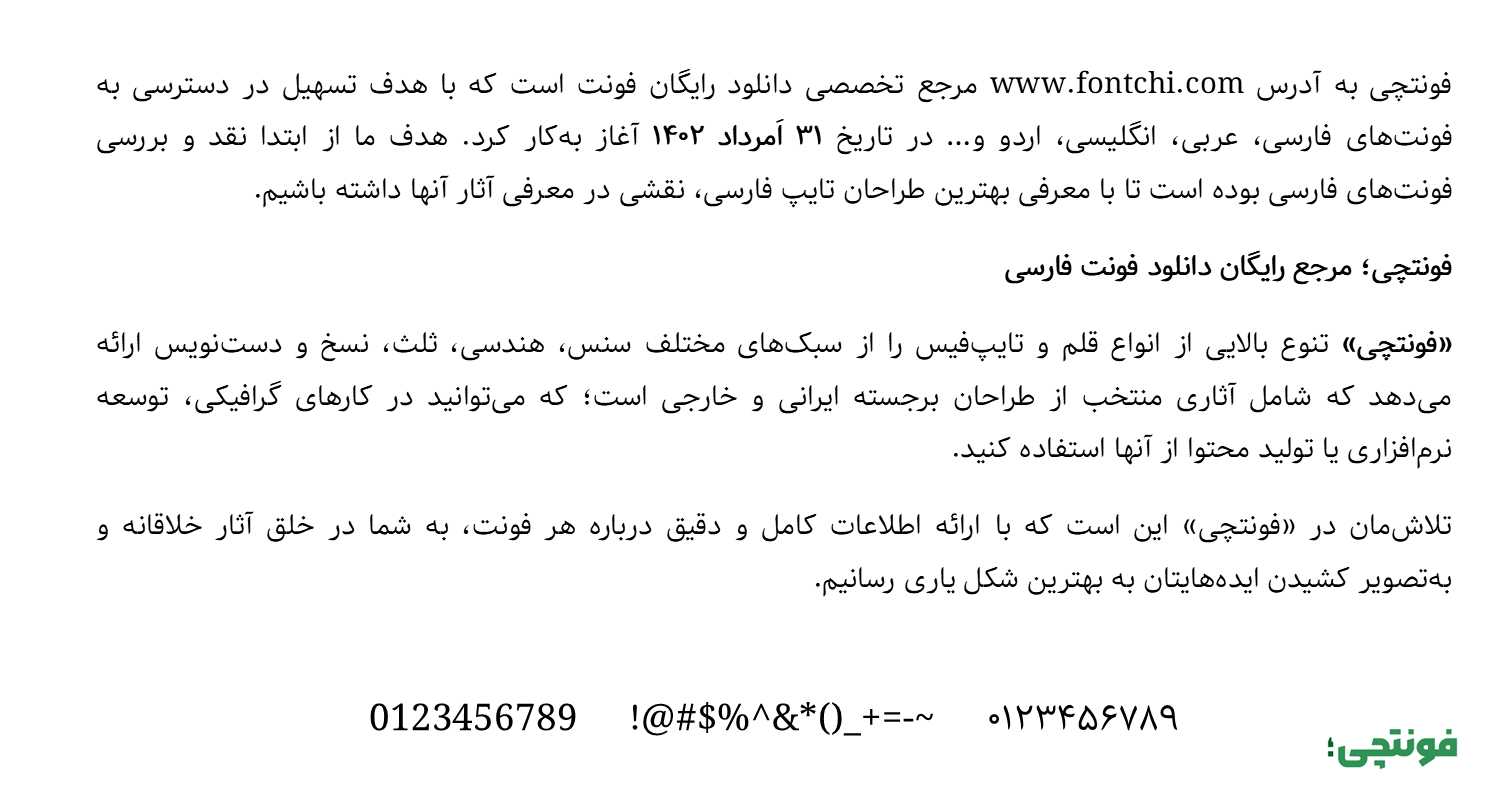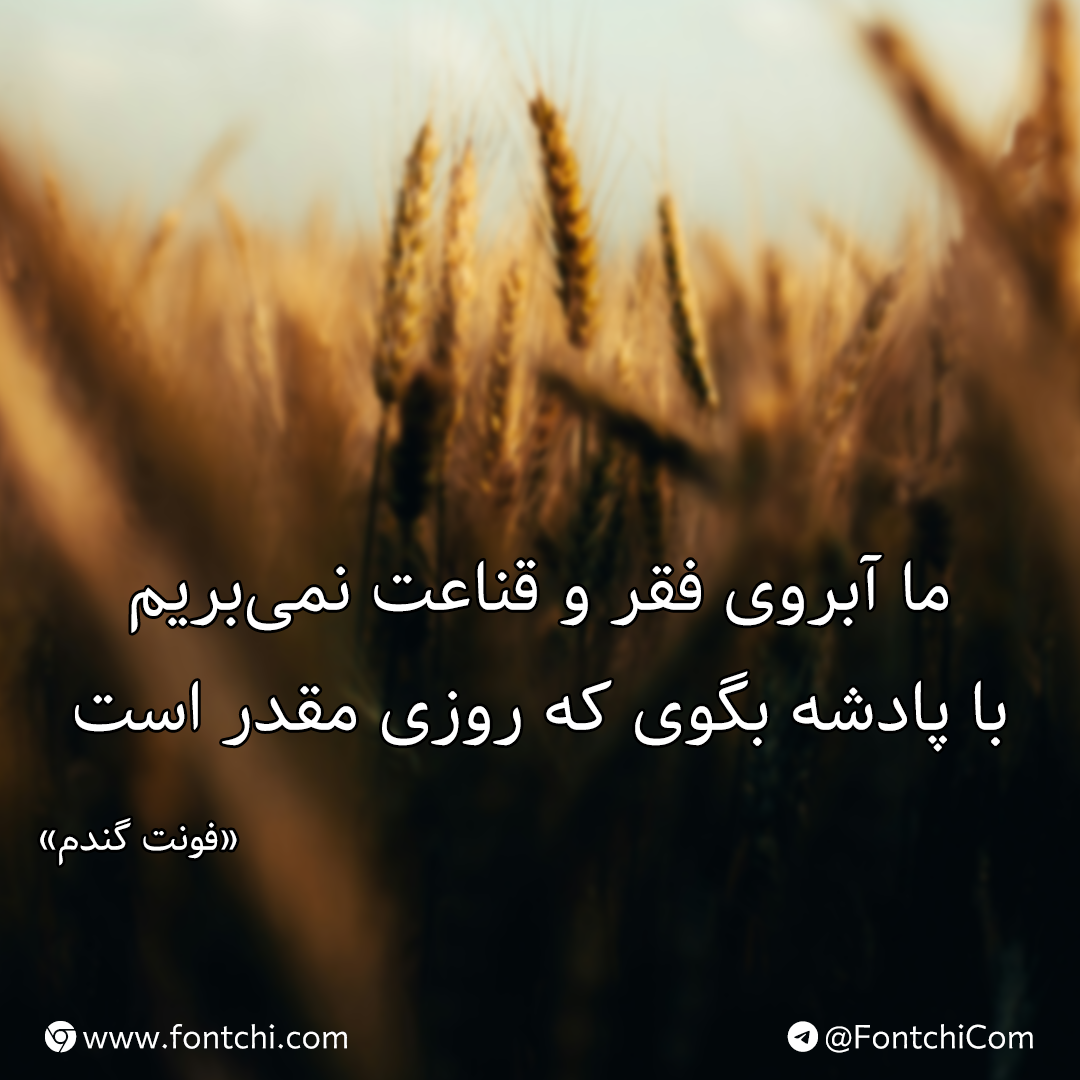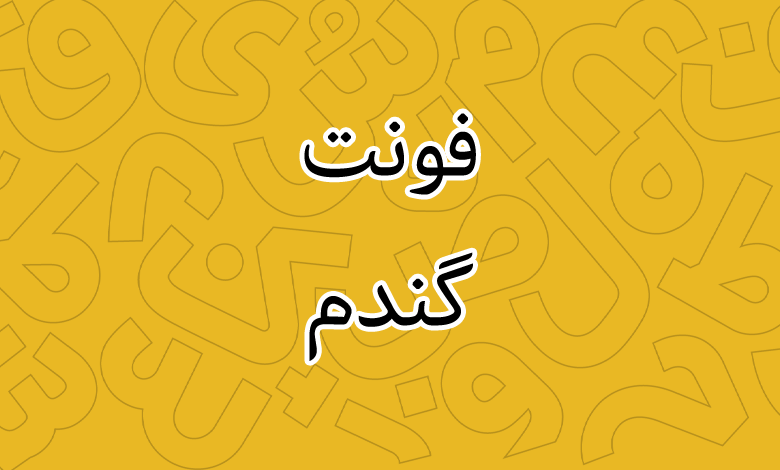
فونت گندم (Gandom)
فونت گندم (به انگلیسی: Gandom) یکی دیگر از قلمهایی است که از طراحی سبک نسخ بهره میبرد. این فونت با ساختار سادهای که دارد میتواند گزینه مناسبی برای استفاده در چاپ و مطبوعات باشد؛ خصوصا روزنامهها و مجلات که خوانایی لازم را برای متون طولانی در اختیار قرار میدهد.
این فونت فارسی رایگان توسط زندهیاد صابر راستیکردار طراحی شده است. این قلم نیز بر پایه فونت صمیم طراحی شده است که خود نسخهای بازطراحی شده از فونت دژاوو انگلیسی است.
در ادامه این نوشته از فونتچی به بررسی فونت گندم پرداخته و با معرفی خلاصهای از ویژگی و امکانات این قلم، محیطهای مناسبی که میتوانید از این فونت استفاده کنید و کاربردهای آن را معرفی میکنیم.
معرفی و دانلود فونت گندم رایگان (Gandom)
فونت فارسی گندم از یک وزن معمولی Regular پشتیبانی میکند. این فونت که از سبک نسخ بهره میبرد، دارای ظاهری جدی است. منحنیها در آن ساختاری نرم دارند و در مقابل شکستگیها در حروفی همچون «د، ذ، ک، گ» دارای ظاهری کاملا جدی هستند.
خوانایی این فونت و طراحی با یک وزن معمولی آن را به انتخابی عالی برای استفاده در متون بلند تبدیل کرده است. خصوصا برای روزنامهها و مجلات که افراد مدت زمان زیادی را صرف خواندن متن طولانی خواهند کرد. طراحی این قلم به شکلی است که در مدت زمان طولانی چشمها را خسته نمیکند.
فونت Gandom علاوه بر زبان فارسی، از زبانهای عربی، انگلیسی و برخی حروف اردو نیز پشتیبانی میکند. چینش حروف در کنار اعراب و کاراکترهای خاص زبانهای خاورمیانهای کاملا استاندارد است و موجب بههم ریختگی نمیشود.